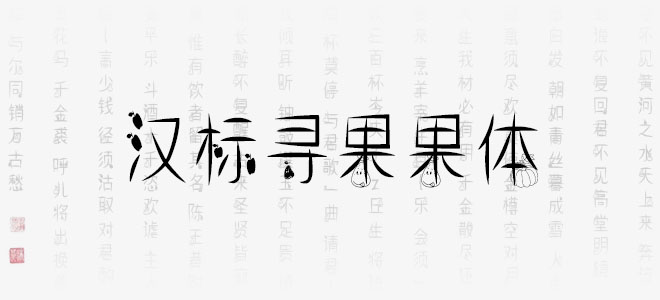
漢標(biāo)尋果果體是漢標(biāo)字庫(kù)推出的一款非常漂亮的藝術(shù)字體,根據(jù)黑體的字形創(chuàng)作而來,作者通過大量加入水果元素設(shè)計(jì)字形,使得字體有在字里找水果感,從而展現(xiàn)美術(shù)視覺感,蘊(yùn)含著深沉的藝術(shù)魅力,能給人以無限的美感,適合應(yīng)用于藝術(shù)設(shè)計(jì)、平面宣傳、包裝印刷、圖形設(shè)計(jì)、網(wǎng)頁設(shè)計(jì)、書法字帖等領(lǐng)域。歡迎喜歡漢標(biāo)尋果果體的朋友前來下載使用。
漢標(biāo)尋果果體